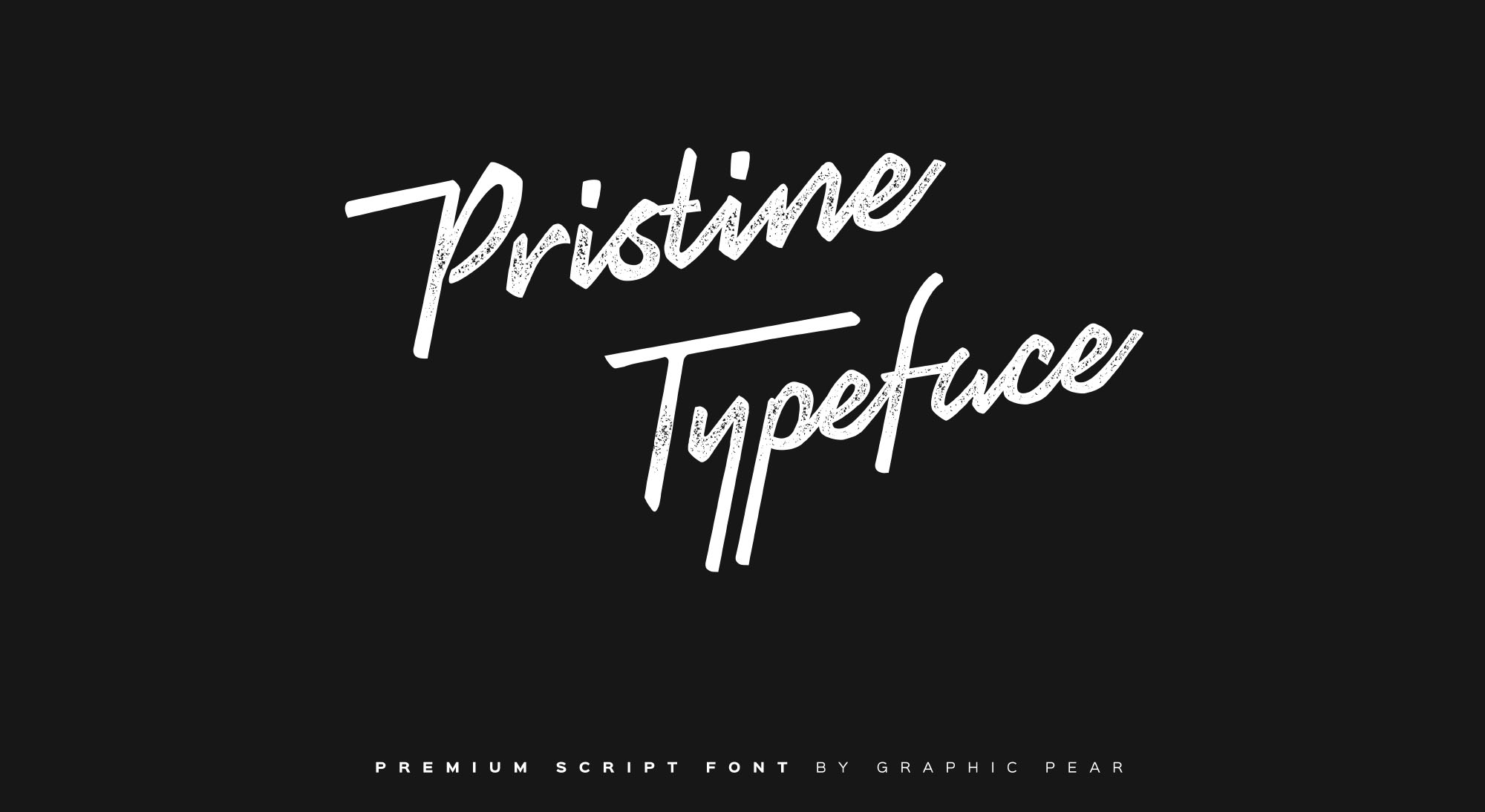
Pristine Script Font – Download Grátis
PristineScript é uma fonte script livre que traz a elegância do estilo clássico do xilogópico à sua página ou projeto. Introduzida pelo designer Hamilton, essa fonte de escrita de alta qualidade não só oferece letras e números, mas também um vasto leque de símbolos, tornando-a ideal para uma variedade de usos gráficos. Seja para cabeçalhos dinâmicos, camisetas criativas, embalagens agradáveis, avisos informativos ou até mesmo selos de evento ou logotípicos personalizados – PristineScript é uma fonte que não só complementará sua identidade visual, mas também adicionará um toque único e autêntico a qualquer projeto. Combinada com seu designer G. Senzana e compartilhada pelo Graphic Pear, esta fonte de escrita segue o caminho do sucesso para aqueles em busca de uma opção confiável para projetos semelhantes.